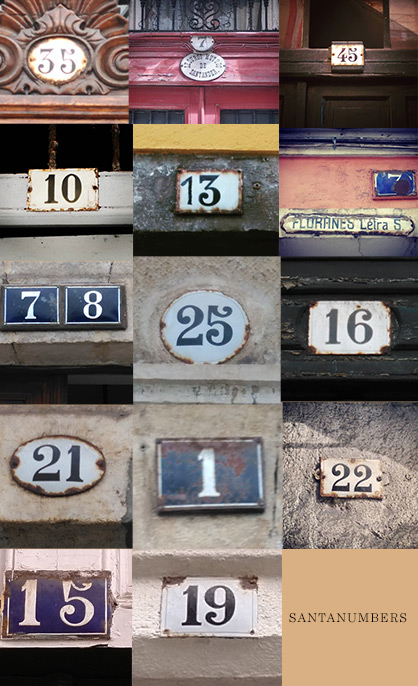
Números de Santander
Entre los números de Santander que bajo el Hastag #Santanumbers del Instagram de Santatipo se recoge ese paisaje visual de la ciudad, destaca una tipografía particular que se repite:
Números de Santander
En su forma recuerda ligeramente a una Bodoni, pero es como está realizado cada número y sus características, lo que la hacen única. Además, casualmente, ningún número es igual porque en muchos casos a la hora de fabricarse los trazados han sufrido algún tipo de alteración. Por otro lado, está el soporte que tiene un protocolo en las formas de las placas y código de color: Fondo azulado (como el del póster) con la tipo en blanco o fondo en blanco con la tipo en negro).
Estos números les podemos encontrar en muchos portales de Santander de las zonas más viejas que se salvaron del incendio. Por lo que todo hace indicar que a finales del siglo XIX o principios del XX existió algún tipo de normativa en estilo y soporte que unificó la señalética de la numeración de las fincas. De este modo se dotó de unidad e identidad visual propia a las calles de la ciudad.
Ahora, a modo de homenaje de esa identidad tan particular, se ha realizado este poster con la recreación de esos números y su particularidades en los trazados, además de color azul dominante en las placas.